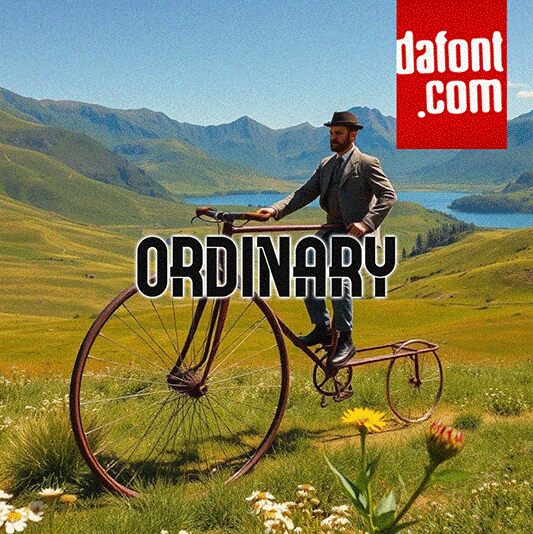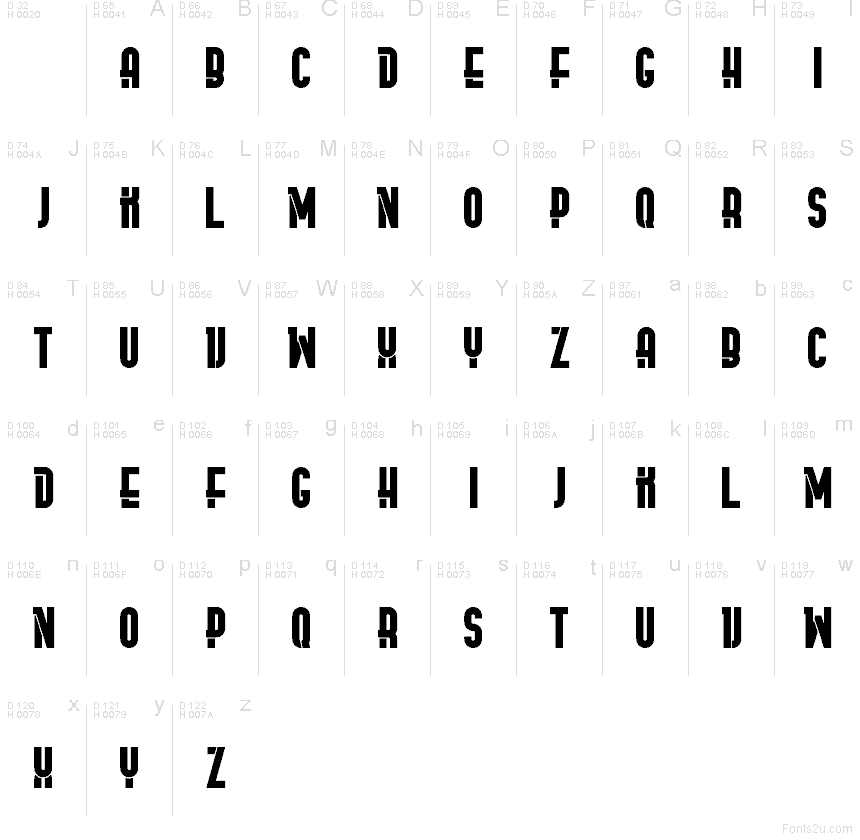
Ordinary Flat di Vladimir Nikolic è un carattere display geometrico in maiuscolo con un ritmo urbano e deciso. Le lettere sembrano ricavate da blocchi solidi, unendo angoli arrotondati a verticali rigide e qualche intaglio netto che impedisce al design di risultare troppo levigato o futuristico.
È perfetto per poster, copertine di album, grafiche streetwear, titoli, testate e brevi progetti di branding in cui questo font gratuito può puntare sulla ripetizione e su spaziature strette. Usalo per titoli brevi, monogrammi o bozze di loghi quando vuoi che le maiuscole comunichino peso e forma, con quel tocco di carattere necessario a evitare un aspetto anonimo.